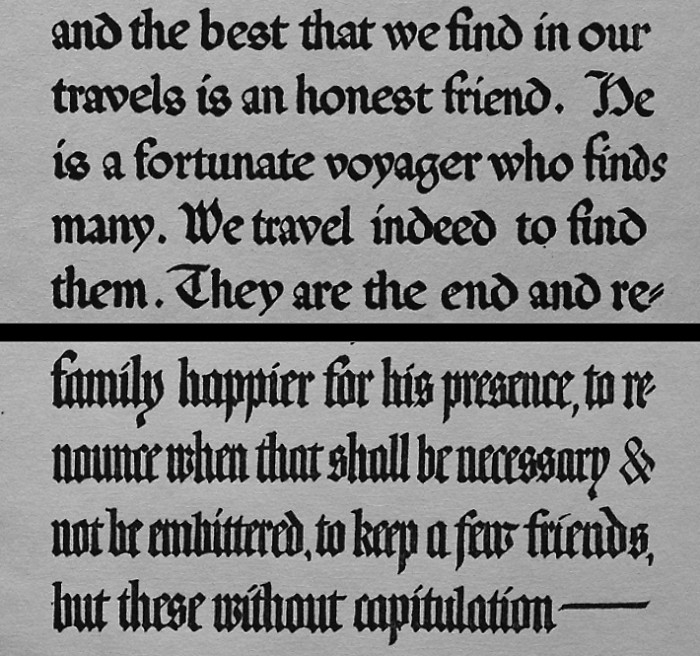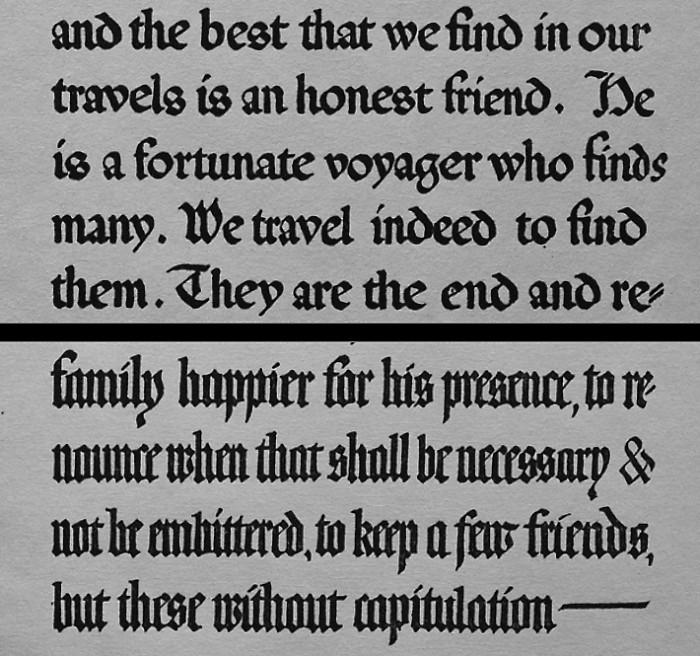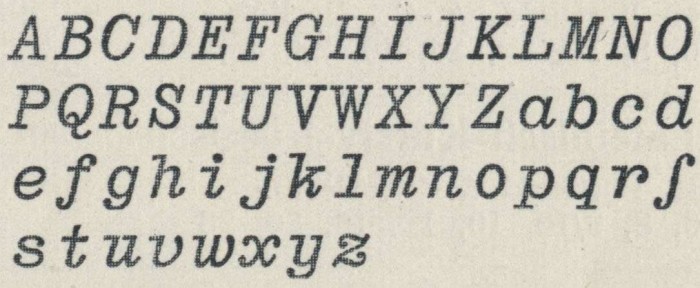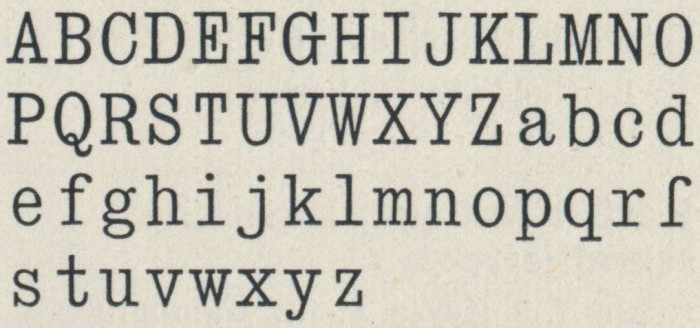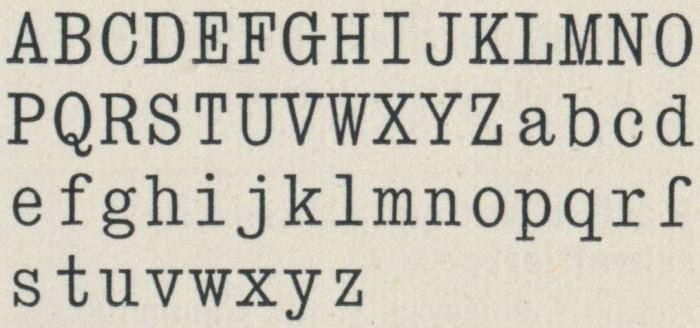
Langes s in heutigen Texten in gebrochener Schrift – notwendig, möglich oder unsinnig?
Das ist ein gutes Beispiel dafür, dass dieses Wissen auch ohne Verwendung auf einem Spiegel-Titel vorhanden ist – also keine Spur von Verblödung  :-o
Mich würde ja mal interessieren, ob es eine Erhebung gibt wievielen Menschen (nicht Setzern) die Regeln vor hundert Jahren klar waren, und wem ein falsch gesetztes s aufgefallen wäre ..?
... und das man als Intellektueller unbedingt regelmäßig Fraktur lesen muss um sich als solchen bezeichnen zu dürfen, halte ich für eine sehr steile These  8-)
Also bitte, vor hundert Jahren waren alle deutschen Tageszeitungen in Fraktur gesetzt, man schrieb Kurrent, es gab nur wenige anderes, nur in Kunst und Wissenschaft kam Antiqua vor, später auch in Mode- und Lifestylemagazinen. Natürlich wäre jedem das falsche s in der Wortmitte aufgefallen, dazu braucht man doch keine »Erhebungen«.
Ich finde die These eigentlich recht gut, aber ich würde sie nicht von regelmäßiger Lektüre abhängig machen, sondern so formulieren: Wer keine Fraktur lesen kann, ist sicherlich kein deutscher Intellektueller. Vielleicht irre ich, aber eigentlich sollte ein Kopfarbeiter die Schulschrift der letzten lebenden Generation nicht für ein Geheimnis oder auch nur eine Schwierigkeit halten. Jeder geübte Antiqua-Leser liest binnen Minuten fließend Fraktur.
Wenn einer keine Fraktur liest und in seinem Umfeld Fraktur nicht üblich ist, dann ist diese faktische Wirklichkeit nicht allgemeingültig.
Aber sicher ist das eine faktische Wirklichkeit. Zähle alle in Deutschland in diesem Jahr erschienenen Zeitungen und und prüfe sie auf auf die Verwendung von Fraktur oder Antiqua. Nehmen alle neu erschienenen Romane und prüfe. Du findest, dass weit über 90% (ich bin mal konservativ ;-) ) Antiqua-Satzregeln benutzen und kein ſ mehr vorkommt. Das ist ein Fakt und das ist die heutige Üblichkeit. Da beißt die Maus keinen Faden ab.
Ob einzelne 8 Stunden am Tag Frakturbücher lesen, ist dabei doch völlig irrelevant. Du hängst weiterhin an dieser Idee, dass der Schriftanwender irgendwie eine kundige Elite in ihren Gewohnheiten bedienen müssten, selbst wenn diese bei der jeweiligen Publikation die absolute Minderheit darstellen. Klar, kann machen. Mir leuchtet aber nicht ein, warum das empfehlenswert sein soll. Warum, sagte ich ja schon mit meinem Versalien-Großbuchstaben-Beispiel. Schrift ist ein Kommunikationsmittel. Ich möchte jemanden erreichen. Nicht selten möchte ich sogar möglichst viele erreichen, möchte eine bestimmte Nachfrage bedienen und möchte nicht selten sogar Geld als Gegenleistung. Warum ich es dabei der Mehrheit der Empfänger schwerer machen soll, um gleichzeitig die Erwartung einer Elite zu bedienen, weiß ich nicht. Dies widerspricht meinem Verständnis von Typografie (und Orthografie, Ausdruck, …).
Den Begriff »üblich« zu definieren, muß man denen überlassen, die alte Schriften lesen, nicht jenen, die einmal im Jahr ein Restaurant mit Fraktur ausstatten, weil das so gemütlich ausschaut oder einen »Spiegel«-Titel, auf dem es um den Nationalsozialismus geht, weil gebrochenen Schriften ganz allgemein idiotischerweise neben der Gemütlichkeit auch der Nationalismus zugerechnet wird.
Nö. Weder »muss« man das, noch ist es irgendwie realistisch. Üblich ist, was eben (allgemein) üblich ist. Und Üblichkeit entsteht in der Masse. Du kannst gern andere Gruppen bilden und sagen »unter Frakturfreunden üblich«, »unter Bleisatzdruckern üblich« oder ähnliches, aber dies wäre dann nicht mehr das allgemeingültige »üblich«.
… weil Abweichungen davon das Bild empfindlich stören und das diesen Lesern lästig ist.
Tja, und dies ist nun eben einfach zunehmend umgekehrt. Für eine große Zahl von Schriftanwendungen ist es immer mehr Lesern heute »lästig« (wie du es sagst), mit historischen Konventionen konfrontiert zu werden, wenn sie nur die aktuellen Satzkonventionen gewöhnt sind. Ich sage das erstmal völlig wertfrei. Wenn du selbst Lästigkeit als Kriterium einbringst, musst du auch akzeptieren, dass Millionen heute klassische Satzregeln als lästig (weil ungewohnt) vorkommen. Und wenn du diese Lästigkeit vermeiden möchtest, würde das in gar vielen Fällen gegen traditionelle Regeln sprechen. Dein Argument verkehrt sich also zunehmend gegen dich, je mehre Jahre vergehen. Und es wird auch durch Einzelanwendungen nach klassischen Regeln nicht aufzuhalten sein.
Als ich in der Wochenendbeilage der Süddeutschen Zeitung vor drei (nicht dreißig) Jahren eine ganze Seite in verschiedenen gebrochenen Schriften gesetzt hatte, kamen etliche Leserbriefe, die mich auf ein paar falsche Schluß-s hinwiesen.
Glaube ich dir gerne. Und die Welt dreht sich trotzdem weiter – hin dazu, dass gebrochene Schriften in allgemeinen Anwendungen nach normalen Antiqua-Regeln und aktueller Rechtschreibung gesetzt werden; dass dies die übliche Schreibweise sein wird; dass die meisten Leser dies als normal, richtig und weniger lästig wahrnehmen werden. Genauso wie beim Verschwinden des ſ aus der Antiqua …
Wie bei jeder Debatte halt – es geht darum zu prüfen, ob Thesen oder Antithesen überzeugender oder (bei faktischen Aussagen) im Zweifel sogar wahr sind.
Ich war mir, ehrlich gesagt, bei Verwendung des Wortes »Verblödung« nicht bewußt, damit eine erörterungswürdige These aufgestellt zu haben.
Was dieses Beispiel zeigen soll, ist mir schleierhaft. In der 1930ern hörte man auch andere Musik und zog andere Kleidung an.
… und wenn man halt einen Film darüber macht, muß man sich Kenntnisse über den damaligen Kleidungs- und Musikstil aneignen. Wo nicht, baut man Anachronismen in den Film ein und multipliziert seine falschen bzw. absenten historischen Kenntnisse beim Zuschauer. Das gleiche gilt für die Typo- und Orthographie.
Und ja: ich spreche von Sachlichkeit und Fakten. Was üblich ist, lässt sich belegen und ist keine Frage von Meinungen. Tendenzen im Einsatz des ſ lassen sich belegen und sind keine Frage von Meinungen. Sachliche Vergleiche zu ähnlichen Entwicklungen lassen sich ziehen. Und so weiter und so fort.